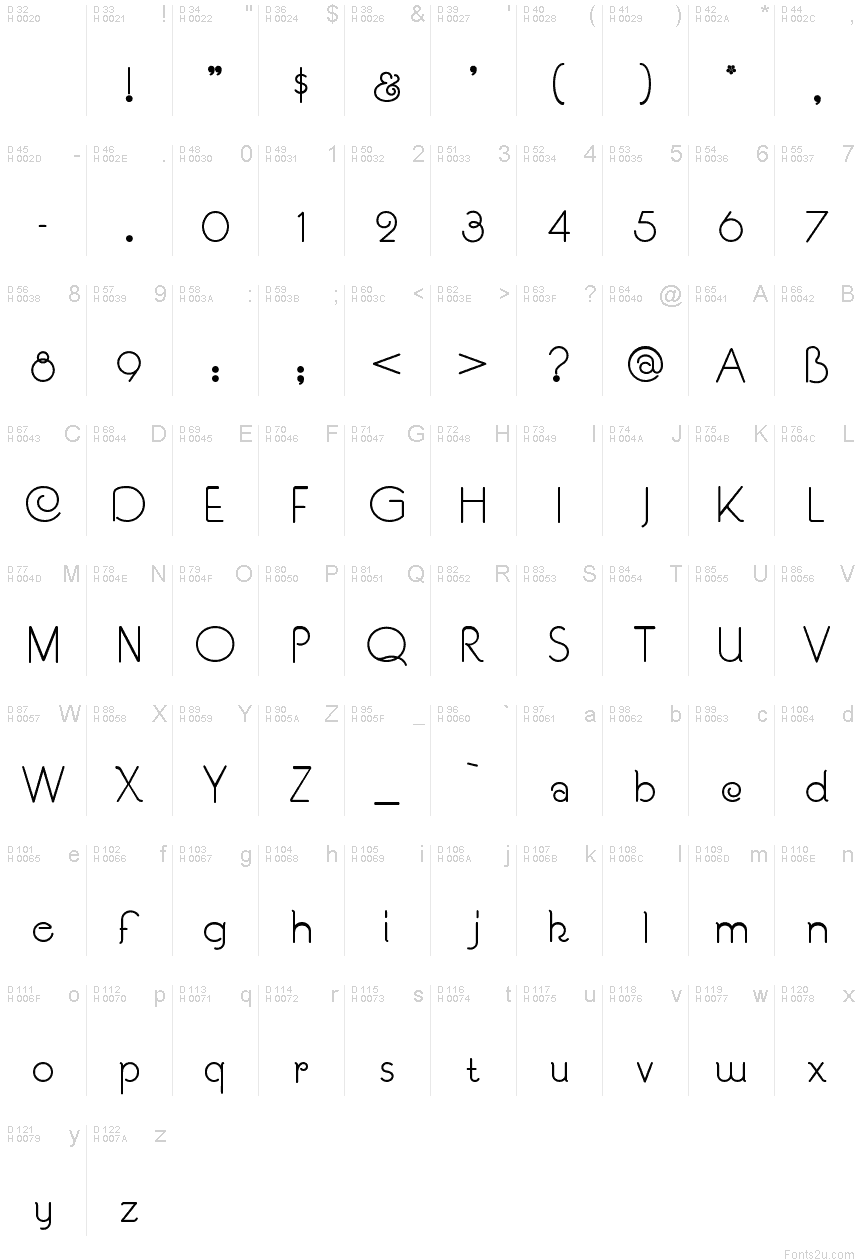
Souci Sans, di Nick Curtis, è un carattere display gratuito con un leggero tocco Art Nouveau. Le lettere appaiono leggere e giocose, con lunghe curve avvolgenti e tratti arrotondati che conferiscono anche alle forme più semplici un aspetto morbido e decorativo, specialmente nel ricciolo a spirale che trasforma il ritmo di una sans standard in qualcosa di più ornamentale.
Si adatta perfettamente al branding di boutique, menu di caffè, copertine di libri, poster e packaging, dove un tocco di fascino d'epoca aiuta a definire lo stile. Essendo un font gratuito, SouciSans dà il meglio di sé in titoli brevi, scritte di copertina e loghi, perché quei dettagli avvolgenti conferiscono alle parole una graziosa impronta disegnata a mano.